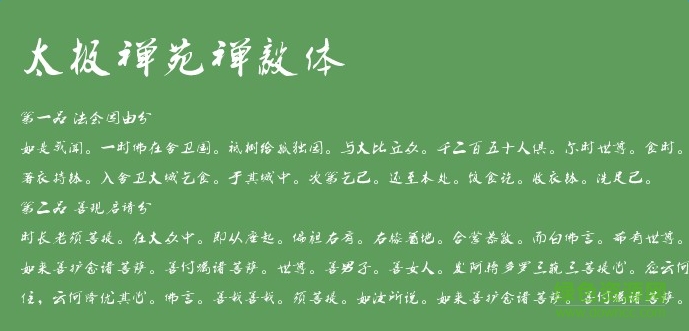
太極禪苑禪毅體字體是一款行草風(fēng)的字體,字體筆畫連綿,結(jié)構(gòu)簡省,字形靈動(dòng),十分俊逸大氣,藝術(shù)設(shè)計(jì)、影視設(shè)計(jì)等都用得到這款字體,喜歡該字體的朋友快來綠色資源網(wǎng)下載吧!
太極禪苑禪毅體是由阿里巴巴太極禪苑擁有版權(quán)的字體,該字體以行草風(fēng)格創(chuàng)作,自然流暢,大方中透露出一種禪文化的陰陽平和,由黃毅先生書寫該字體原稿,由葉根友字體團(tuán)隊(duì)制作。